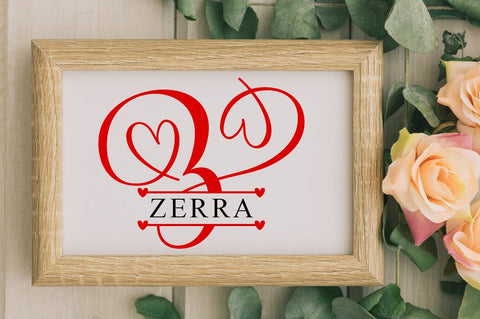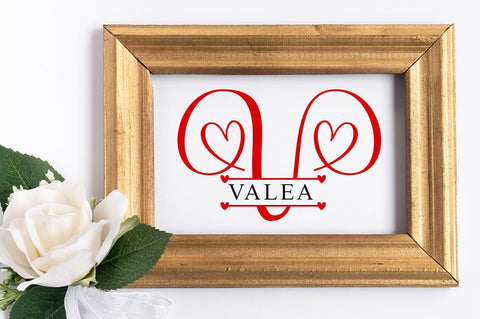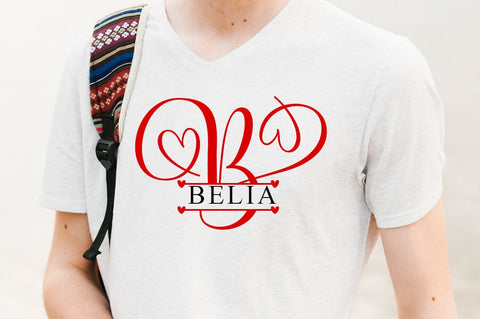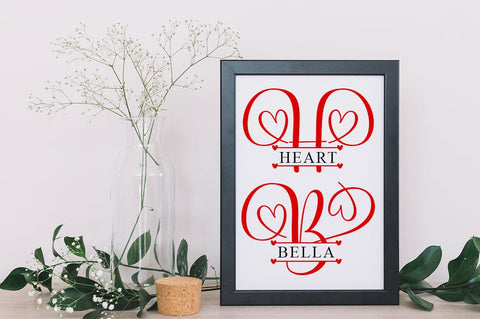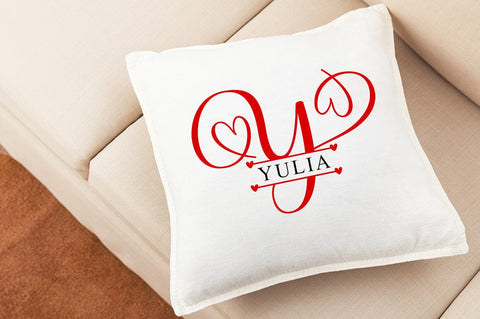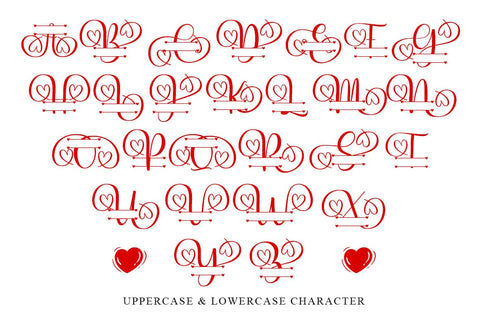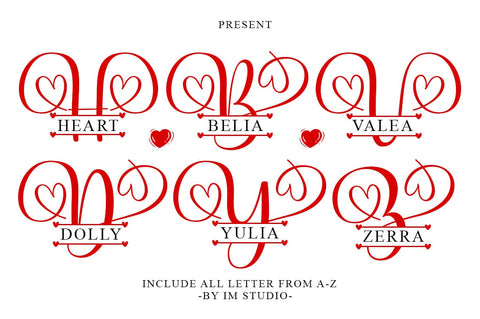
Heart Monogram
Heart Monogram adalah font dekoratif yang elegan, dengan ornamen yang indah. Jatuhkan cintalah dengan nuansa autentiknya dan gunakan untuk membuat undangan pernikahan yang cantik, karya seni yang indah, kiriman media sosial yang menarik, dan kartu ucapan yang lucu.